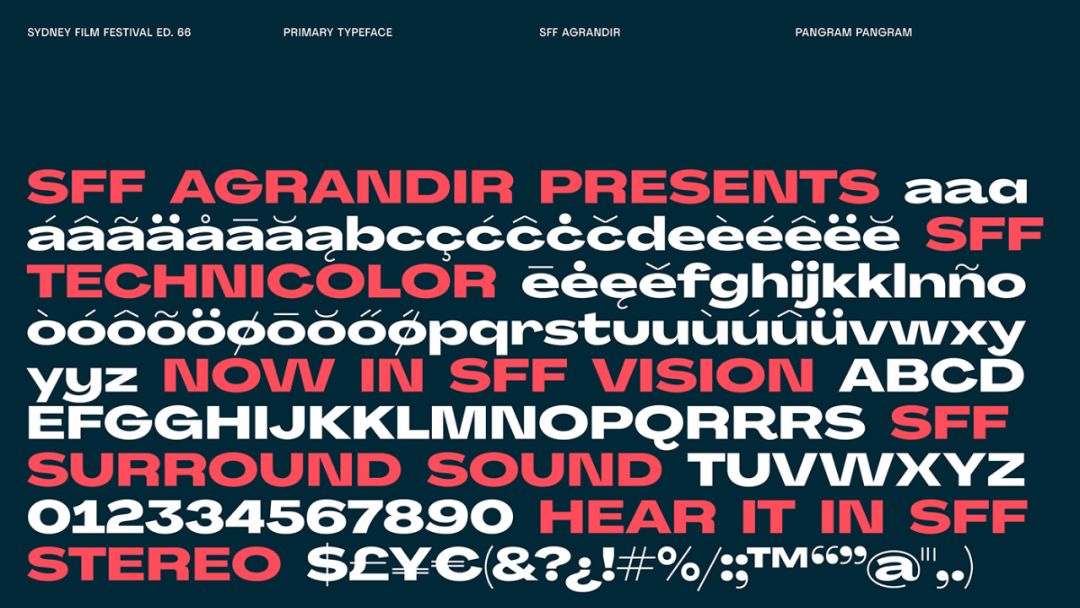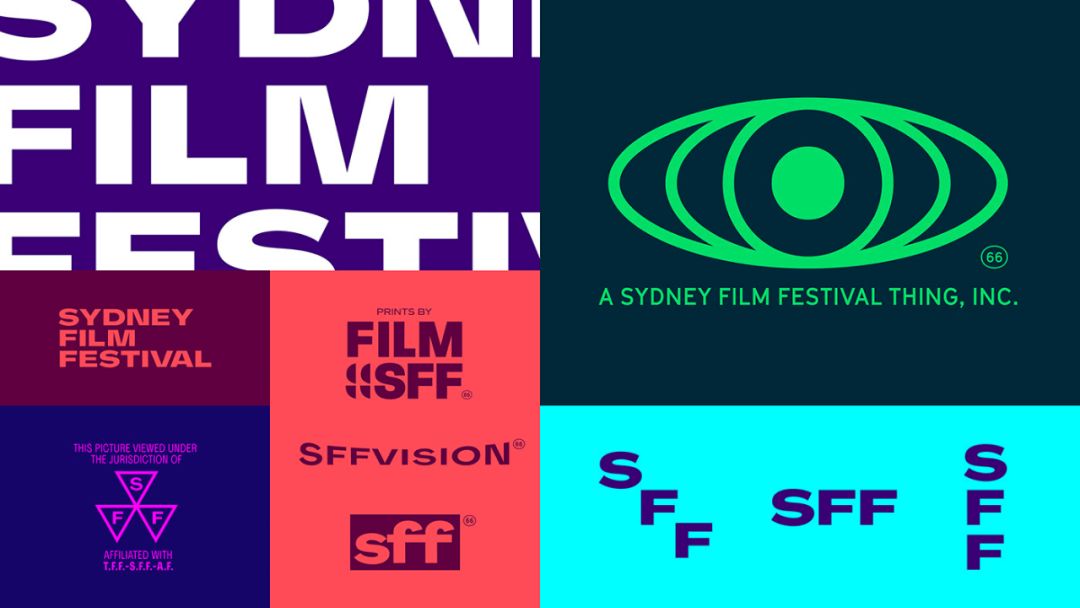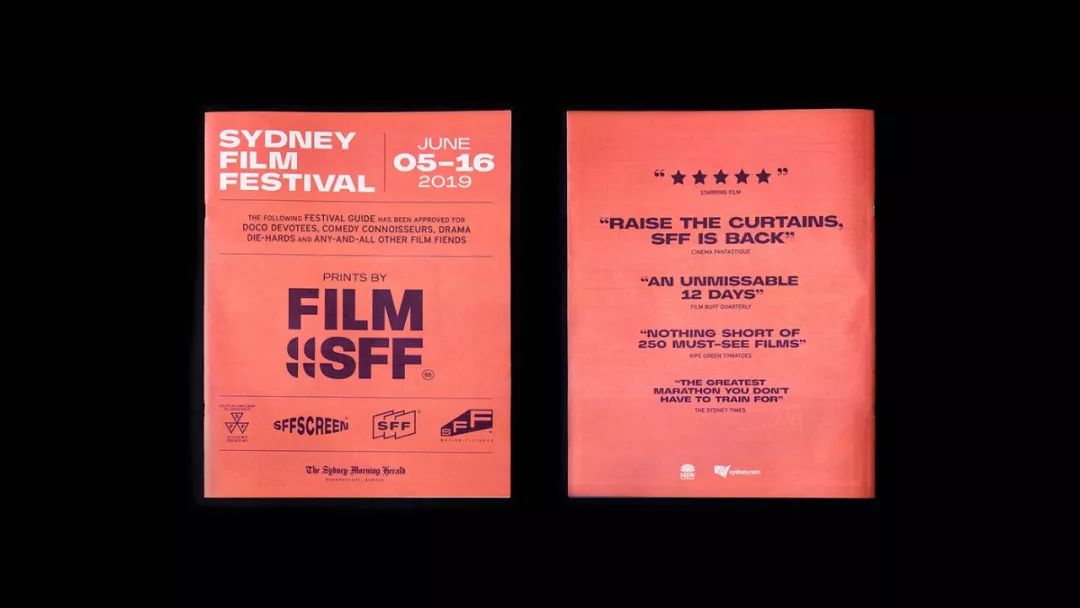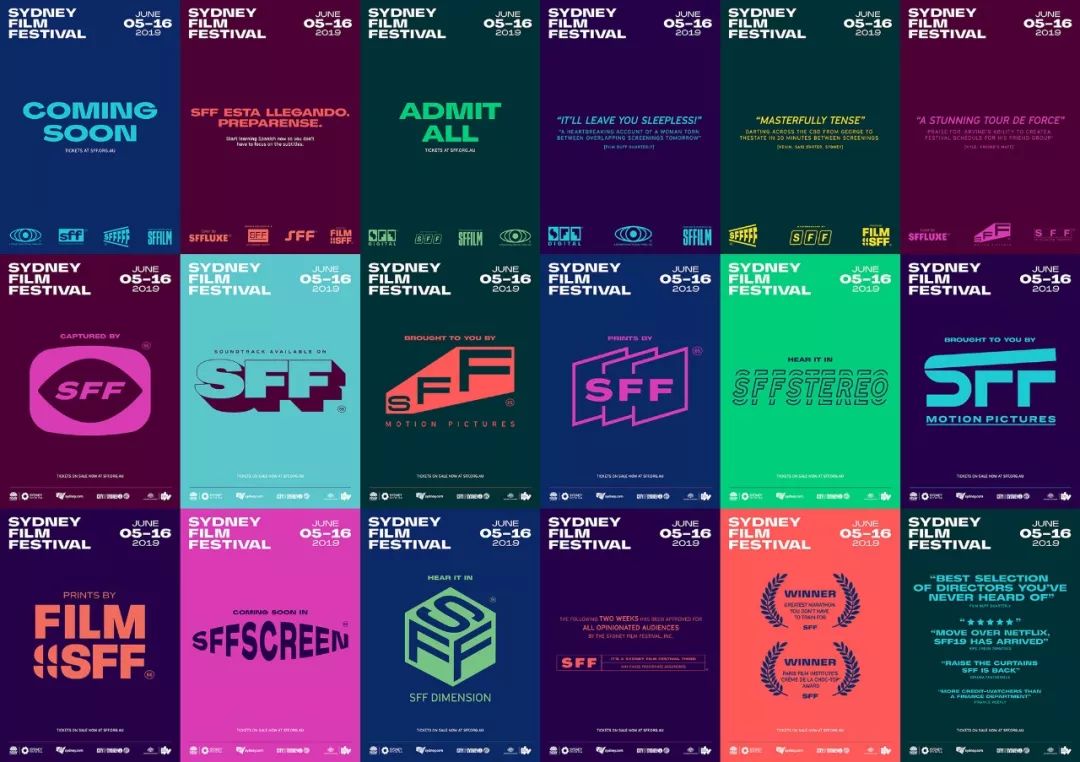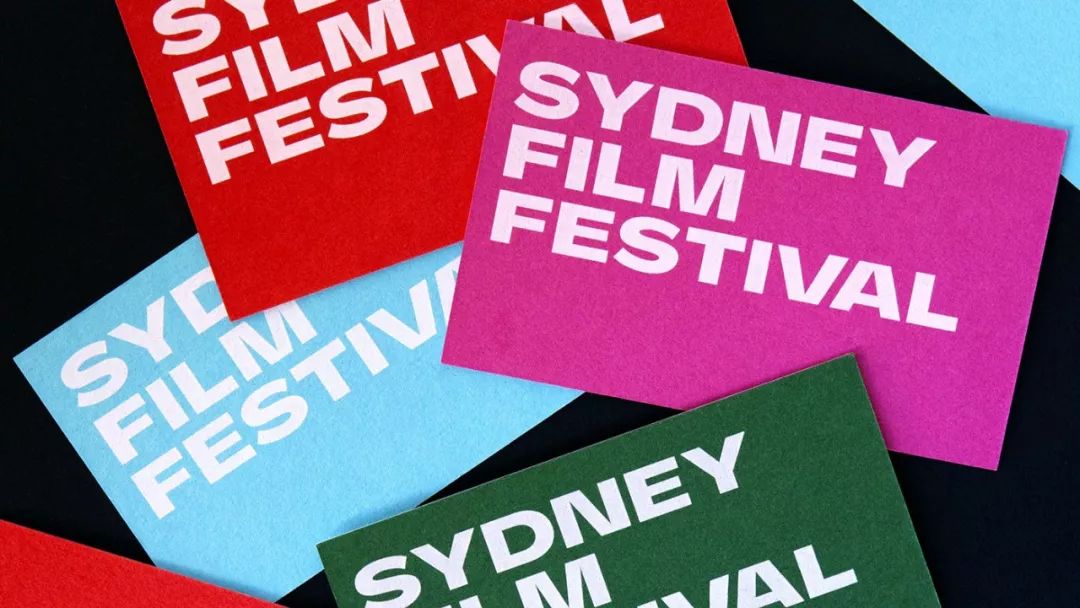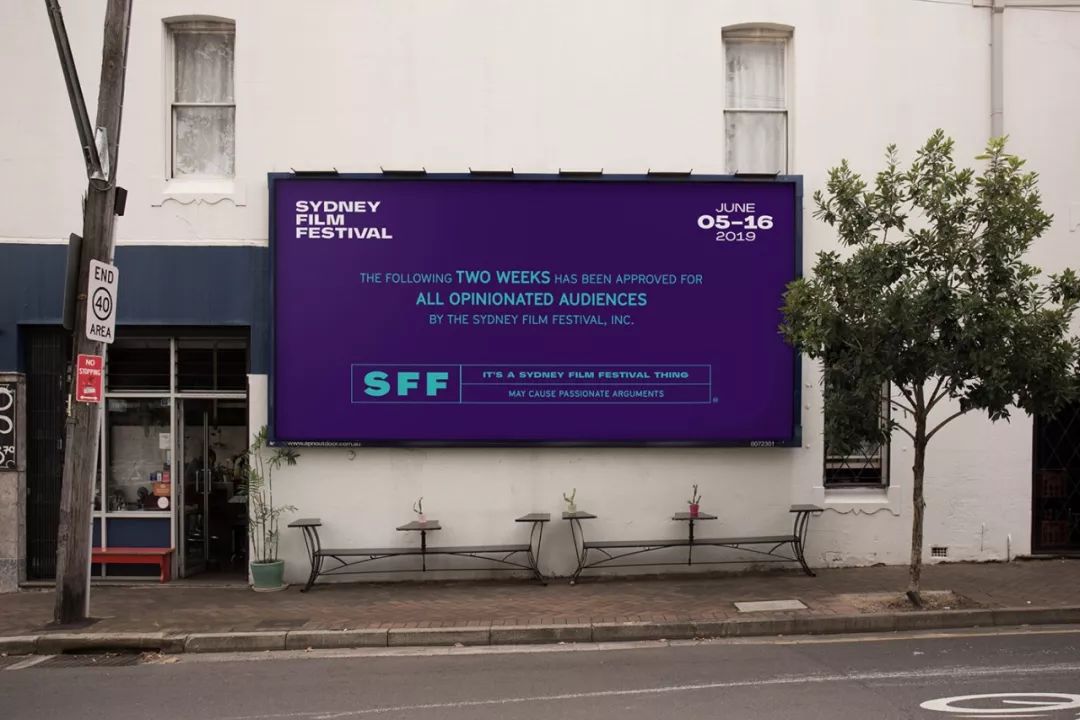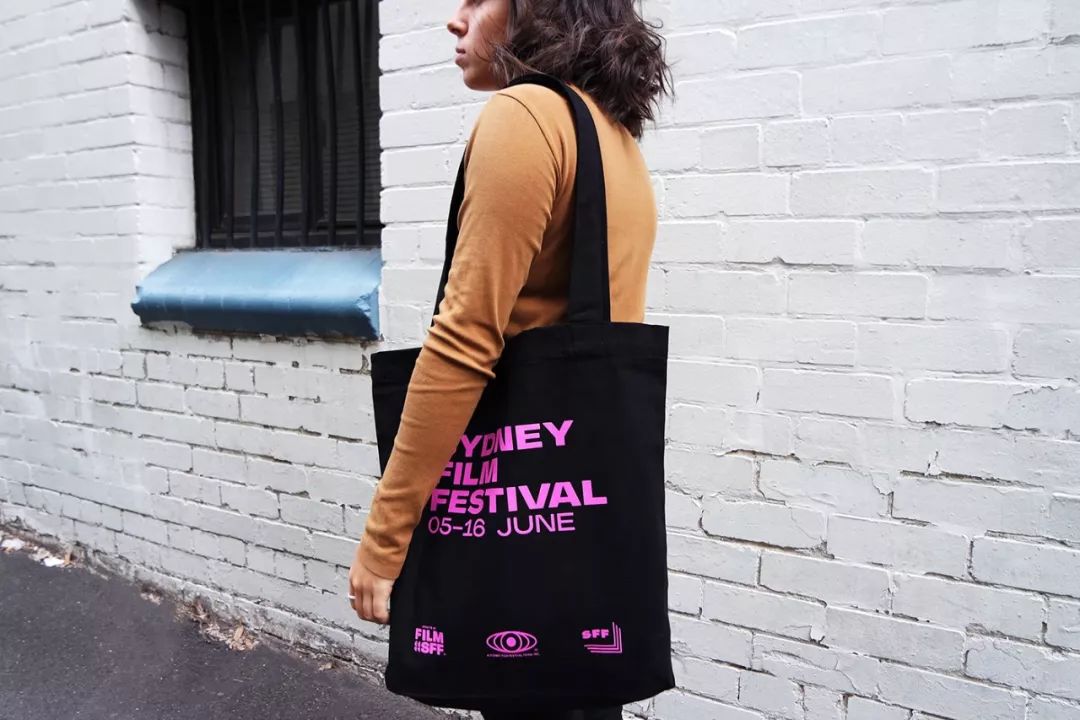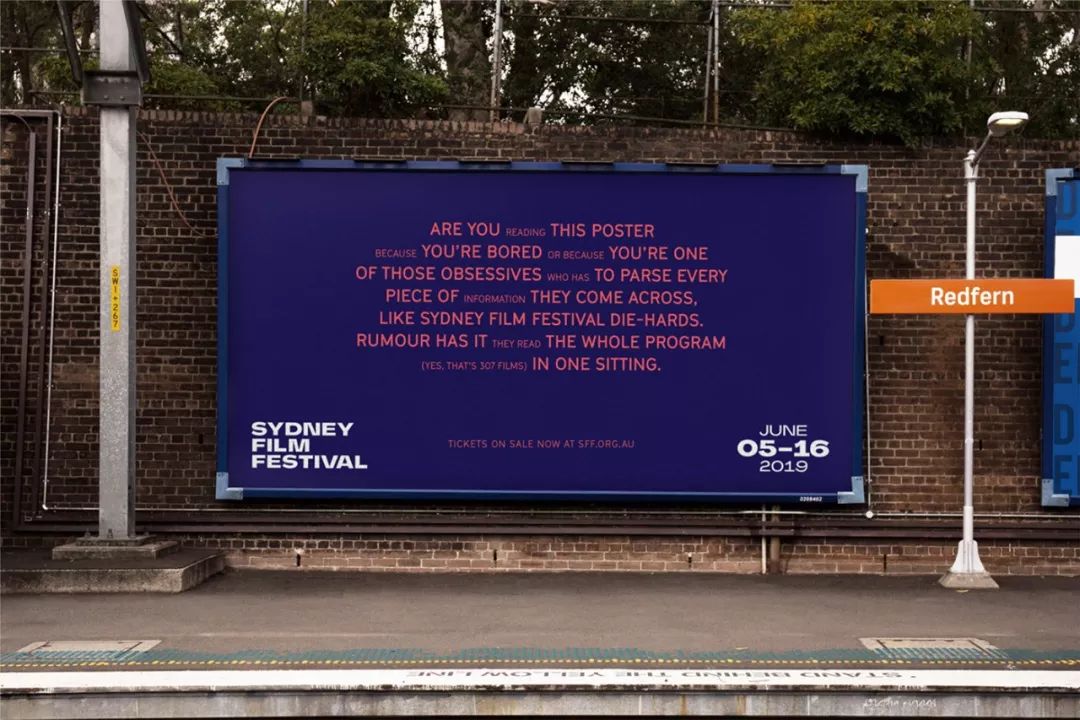
你请我设计一套VI?我免费送你30个LOGO!今天说的就是悉尼电影节。
悉尼电影节(Sydney Film Festival)是一年一度的竞赛型电影节,创立于1954年。悉尼电影节每年6月在澳大利亚悉尼的各个相关场所举办,在为期12天的时间里,放映超过200部的电影,最后评选出12部“勇敢、大胆和前沿”的电影作为最终的获奖影片。
2019年悉尼电影节于6月5日至6月16日在悉尼的九家电影院展开,共放映了来自58个国家的307部伟大而新奇的电影,其中有33部属于全球首映。
今年悉尼电影节启用了新的视觉形象,设计来自本土设计公司 For the People 设计机构。
悉尼电影节旧LOGO(上图左)是没有一个发光的无衬线字母“D”,在黑色的背景下,它就像是电影院里一块亮着的影幕。
新LOGO用的是另一种无衬线字体,这种略显古怪的字体名叫Agrandir。
虽然悉尼电影节的新字标看上去有点平庸,缺乏特色,但是 For the People 另外“免费”为电影节设计了30个延伸徽标,这可是一个大大大惊喜啊!
这些徽标以悉尼电影节的缩写“SFF”为主要元素,参考了上世纪70-90年代电影和电视节目标志、以及Betamax和VHS录像带上的标识,给人以一种怀旧的感觉。
根据徽标的借鉴样式,主要可以分为四大类:屏幕、声音、关联和杂项,For the People 还为此设计了动画效果。
当徽标广泛应用在电影节的各种场合时,它们是如此地无厘头,却又恰如其分地为电影节和所有电影代言。